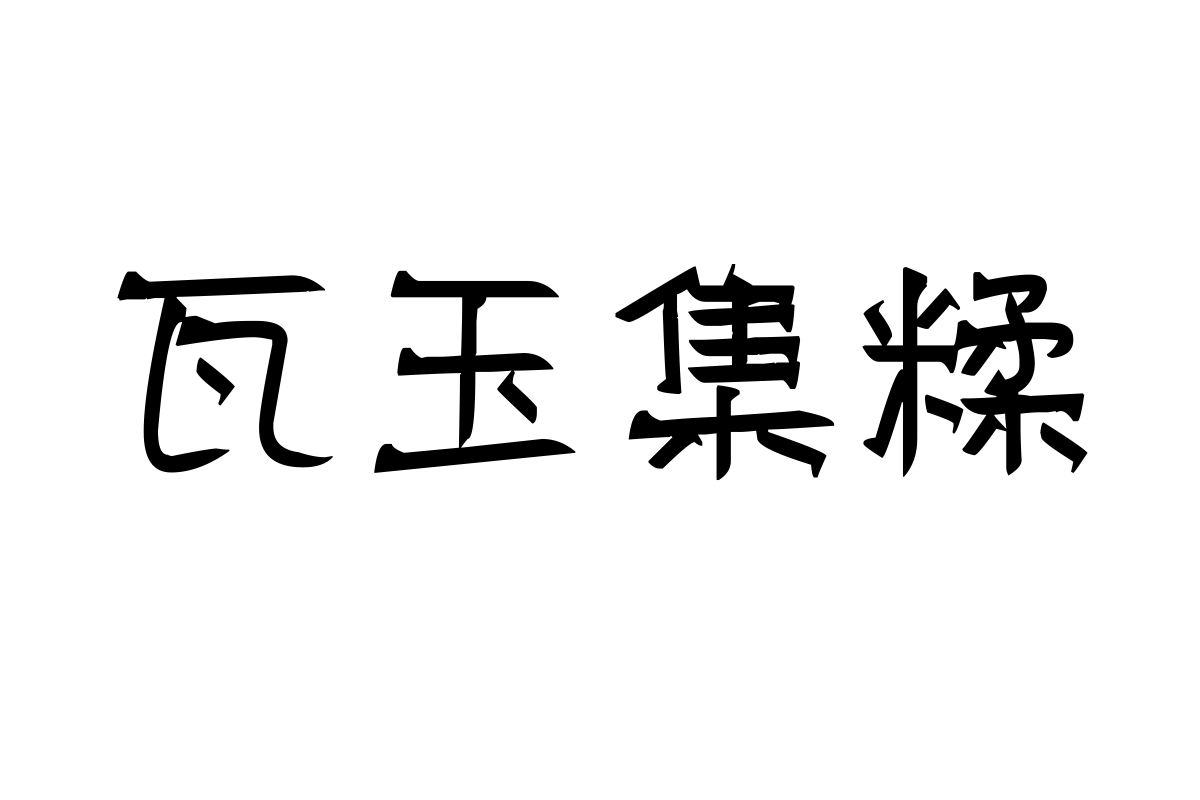
汉标宋刀体是一种书法字体,由书法家王学军于2014年创作。这种字体以其独特的笔画和结构特点而受到关注,具有很高的艺术价值和收藏价值。
汉标宋刀体的笔画粗细变化丰富,线条流畅自然,给人一种古朴典雅的感觉。同时,这种字体的结构也颇具特色,笔画之间的连接紧密,使得整体视觉效果更加和谐统一。此外,汉标宋刀体的书写速度较快,适合用于日常书写和书法创作。
总之,汉标宋刀体是一种极具特色的书法字体,具有很高的艺术价值和收藏价值。